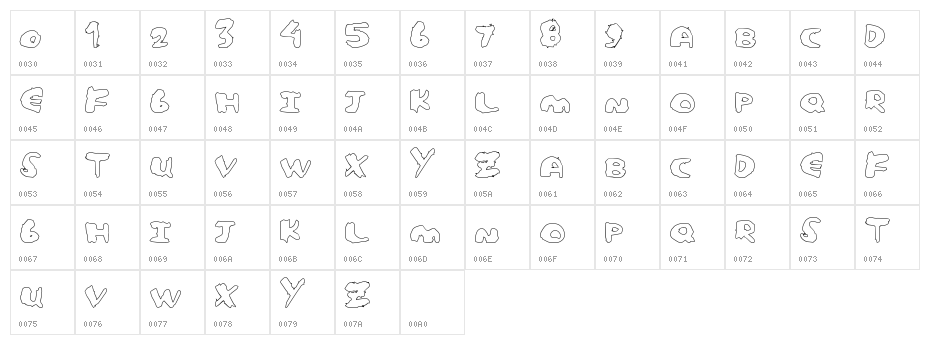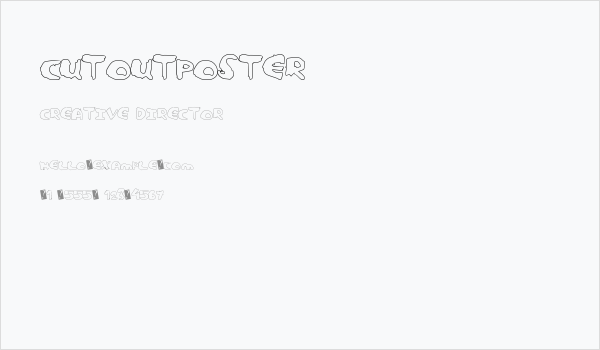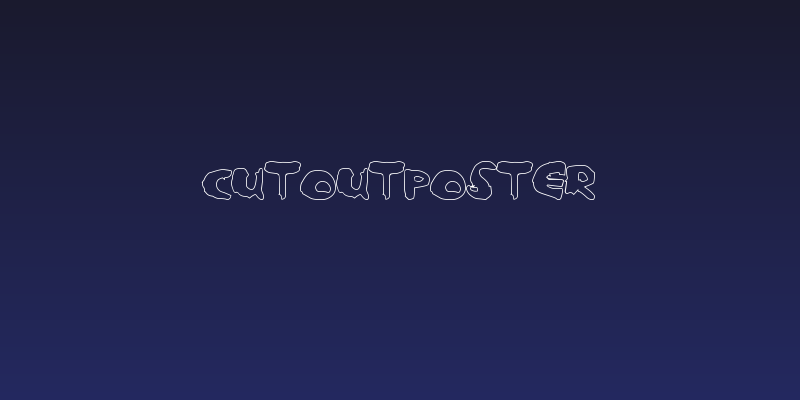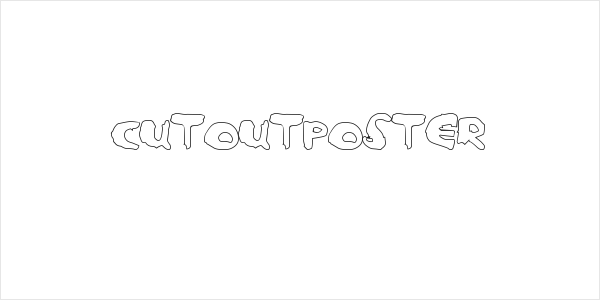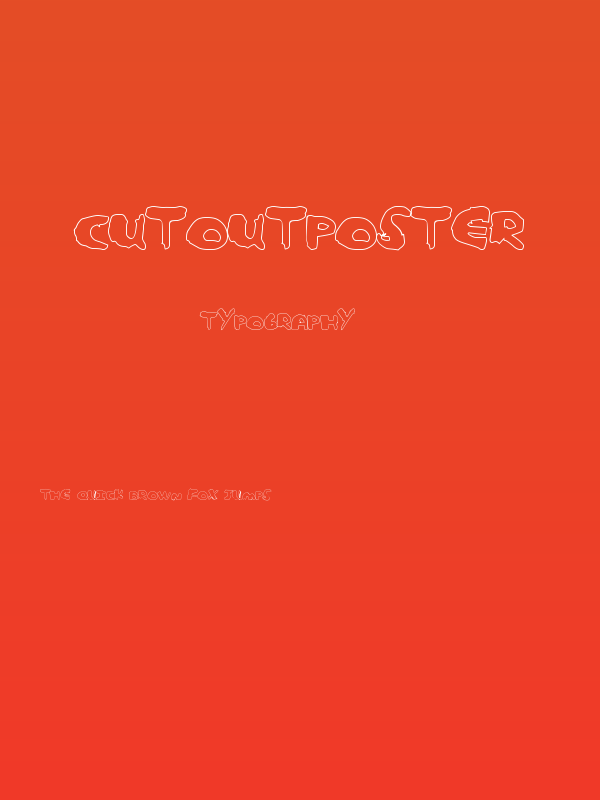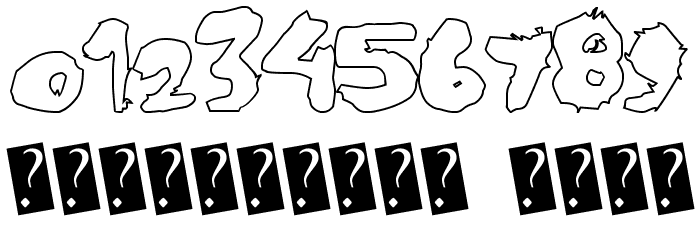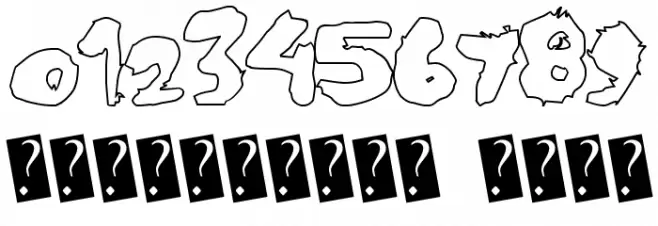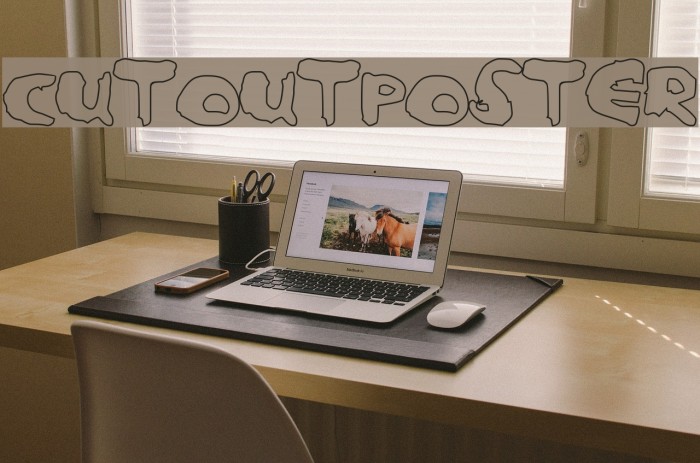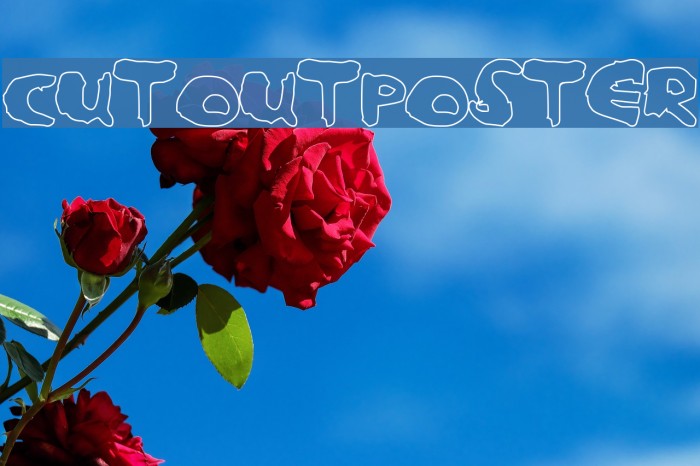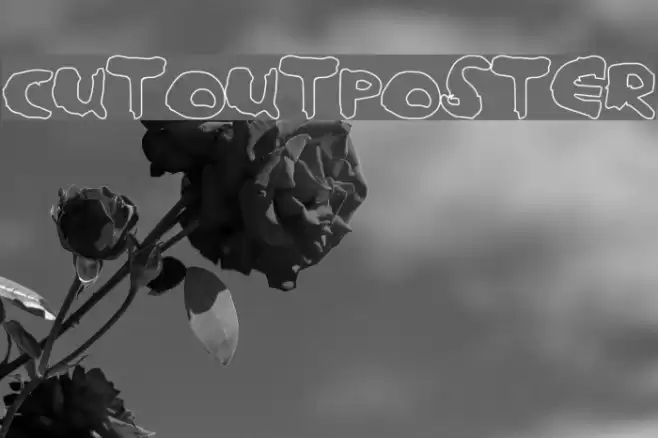
CutoutPoster Font
| Caso de uso | Headlines, Posters, Creative Projects |
| Projetos propostos | Ideal for children's book covers, playful posters, arts and crafts projects, and any design that requires a whimsical and creative touch. |